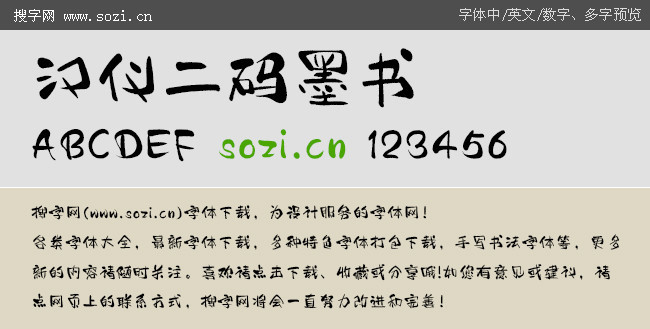
漢儀二碼墨書
搜字網(wǎng)給大家提供一款漢儀二碼墨書中文字體下載,漢儀二碼墨書是一款手寫風(fēng)格的中文藝術(shù)字體,該字體筆觸較為粗實,字體圓潤可愛,適合應(yīng)用于藝術(shù)設(shè)計、平面宣傳設(shè)計、網(wǎng)頁設(shè)計、海報設(shè)計等等應(yīng)用。(本字體為個人非商用版,如需要商用請聯(lián)系漢儀公司購買版權(quán))